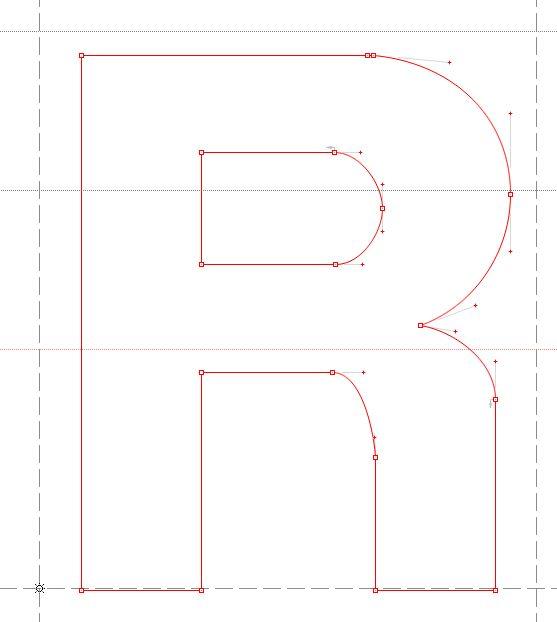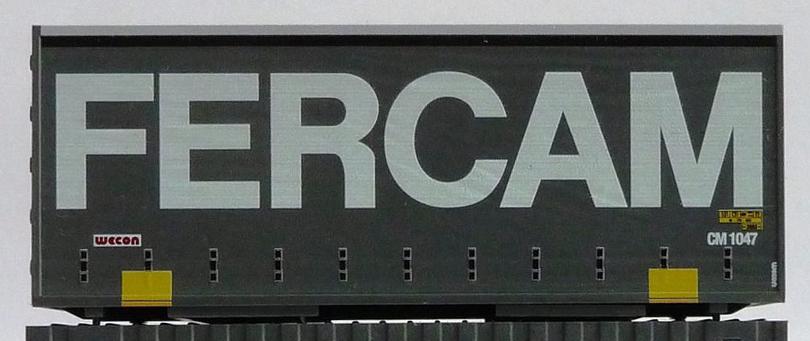
Schrift von Logistikunternehmung FERCAM gesucht
Auf den Autobahnen sieht man immerzu LKW mit dem großflächigen Schriftzug "FERCAM".
Wenn man sich das "R" ansieht, weiß man, dass es nicht die Helvetica sein kann.
Um welche Schrift handelt es sich?
Das wird ein Logo sein. Eventuell standen "Berthold Standard" oder "Europa Grotesk" oder ähnliche Pate …
Zumal es dieses Logo seit Ende der 70er-Jahre gibt, sofern das Bild aus der Unternehmensgeschichte nicht neueren Datum ist.
Frage mich bei diesem "Logogramm" nur, ob es für jenen Gestalter wirklich notwenig war, das "R" so leiden zu lassen? Wie sähe das mit einem schrägen "Abstrich" spiegelbildlich zum "A" aus?
Warum entsteht nun dieser optische Eindruck?
• Weil die Spannung des "Anschlussbogens" das "Beinchen" nach innen zieht?
• Weil das R als Rechteck wahrgenommen wird und die äußere Beichenkannte zum überstehenden "P-Bogen" verlängert wird?
• Der Einfluss des C? Oder?